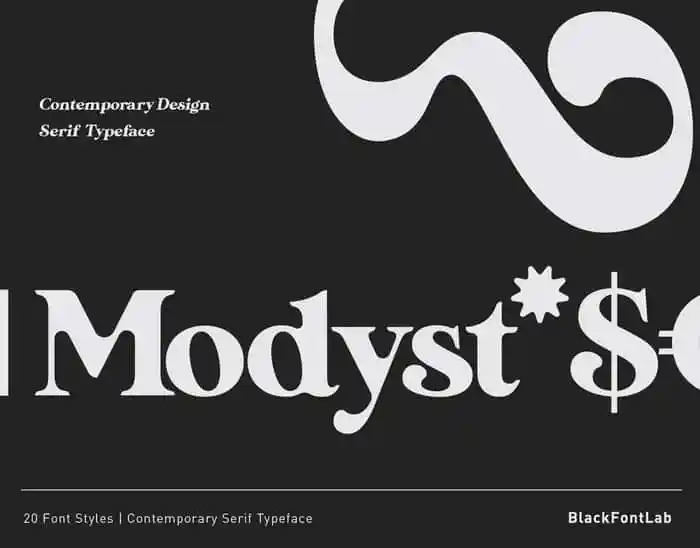
Modyst Serif Font – Fonte Grátis
Modyst Serif Font – Download Grátis
Modyst Serif Font
A Modyst Serif Font é uma novidade no mundo das fuentes tipográficas que traz alegria aos seus projetos. Com suas curvas suaves nos cantos dos carateres, ela se destaca como um tipo moderno e divertido. A fonte incorpora detalhes sutis nas bordas, conferindo um aspecto encantadormente elegante e bonito. Suas aparências são tão versáteis quanto suas aplicações podem ser: desde designs de impressão até logotipos, capas, apresentações, anúncios ou qualquer projeto envolvido em marketing e identidade visual. A fonte vem com 20 estilos distintos, cada um oferecendo uma experiência única. Ela é ideal para quem busca não apenas qualidade de design, mas também diversão e originalidade no trabalho que está realizando. A Modyst Serif Font é perfeita tanto para aqueles que buscam expressar sua personalidade através do texto quanto para aquela pessoa que quer criar um design memorável e alegre. Escolha a melhor versão da fonte Modyst Serif para seu próximo projeto, pois ela certamente vai trazer uma dose de encanto e criatividade à sua arte visual.